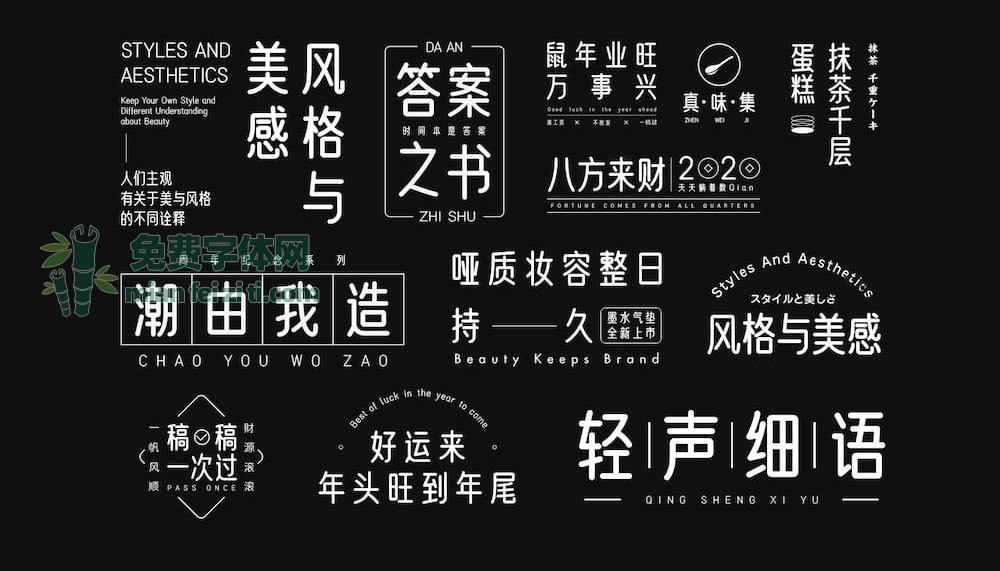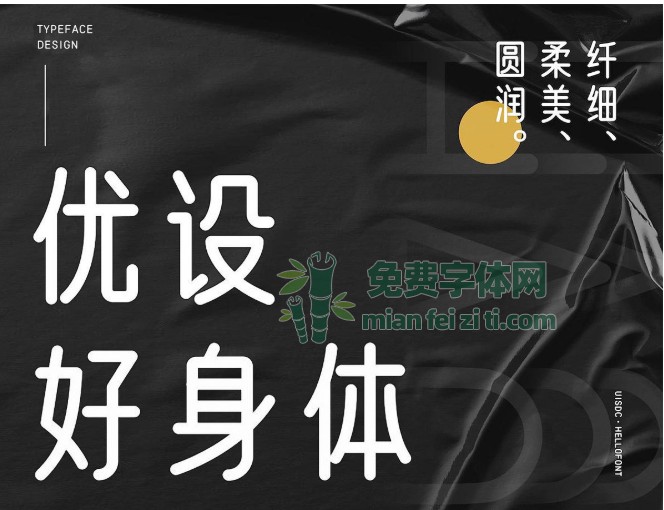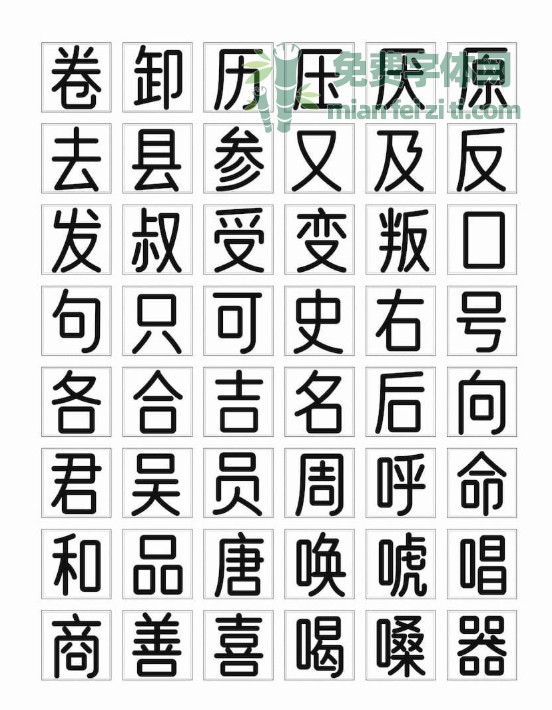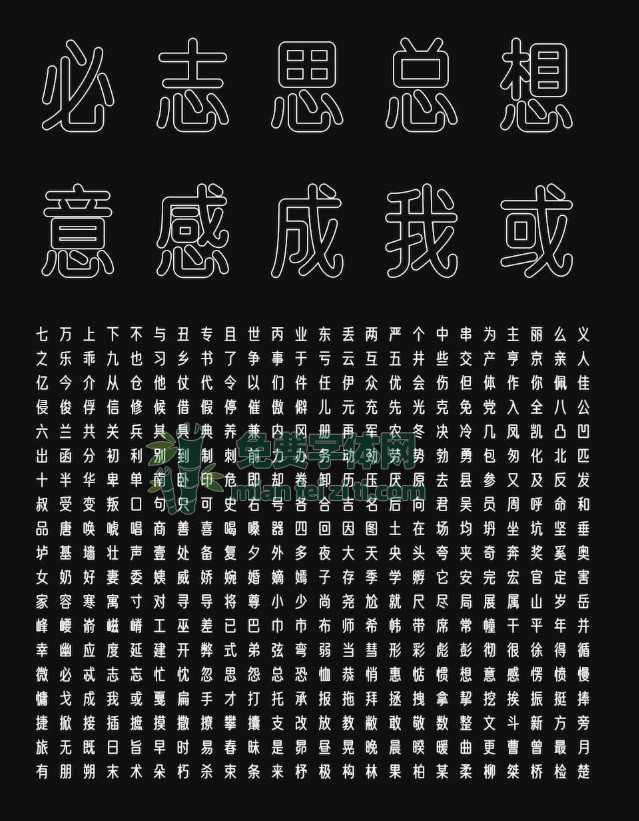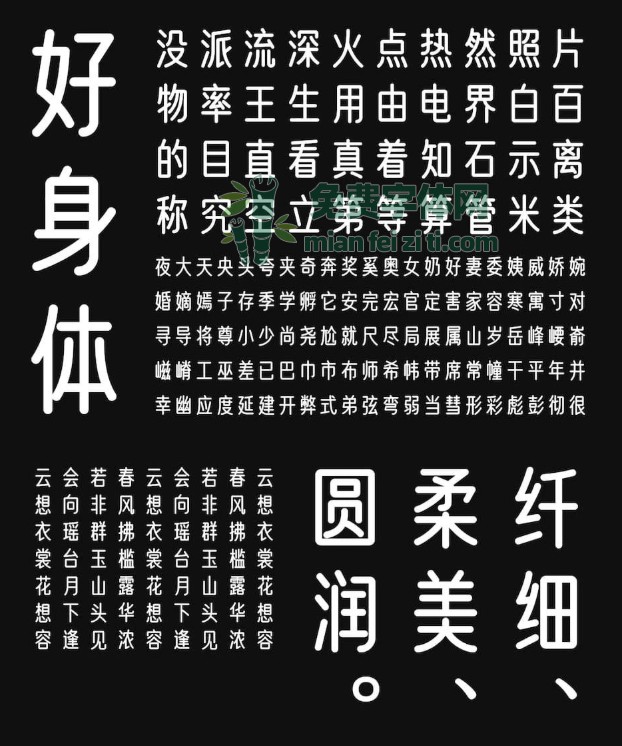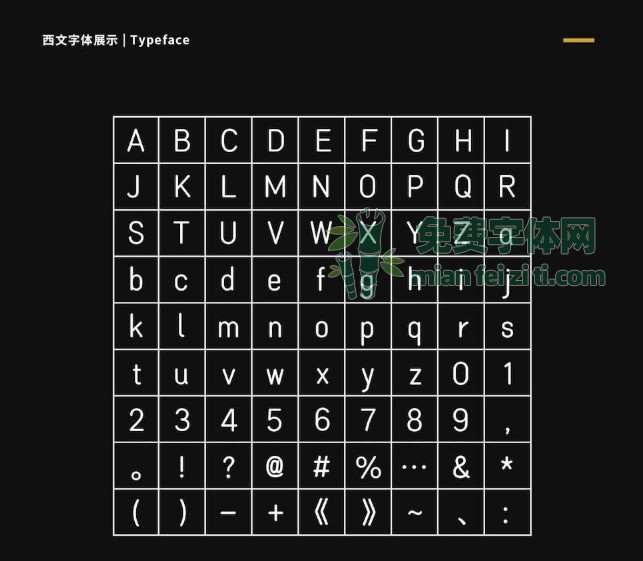
优设好身体-优设第二款免费商用中文字体下载
自从优设联合字由发布第一款免费中文字体「优设标题黑」后,从各个媒体上都能看到这款字体的身影。
好的字体不用多说!这不,优设第二款免费商用中文字体也隆重发布啦!
这款字体的名字就叫做:
优设好身体
优设在完成前期 300 多个基础字型、字母及符号的创意与规范后,字由特意邀请了一群优秀的字体设计师,包括阿里巴巴普惠体设计师陶一泓、汉仪阿尔兹海默病体设计项目负责人卢鑫亚、汉仪锐智字体设计师石凯等,从字库角度出发,完善优化字型,完成了 6000 多个字型的制作,并用了大量时间来进行产品化和字体细节方面的优化。
跟命名优设标题黑不同的是,这款字体命名很有趣,本来字体的名字在 2019 年 10 月份就定下来了,初心是希望设计师用了这款字体以后,能够减少改稿的次数,少点熬夜,有个好身体,更有个好身材。
可是却遇到了这次新冠疫情,让这款字体的命名又多了一层特殊的意义。病毒肆虐,一切都是浮云,唯有好身体才能守得云开见月明,优设和字由希望大家都如这款字体的名字一样,平平安安、健健康康!
「优设好身体」是一款亲和力、现代感极强的专业美术标题字体。
它以圆体字型为基础,通过瘦高的字面、偏向几何的曲线,让整宽字体富有亲和力和时尚感。
在同样的面积里,更窄的字面就意味着能容纳更多的信息,所以这款字体非常适用在需要体现亲和力与时尚感的各类品牌宣传广告和产品包装设计的标题上。